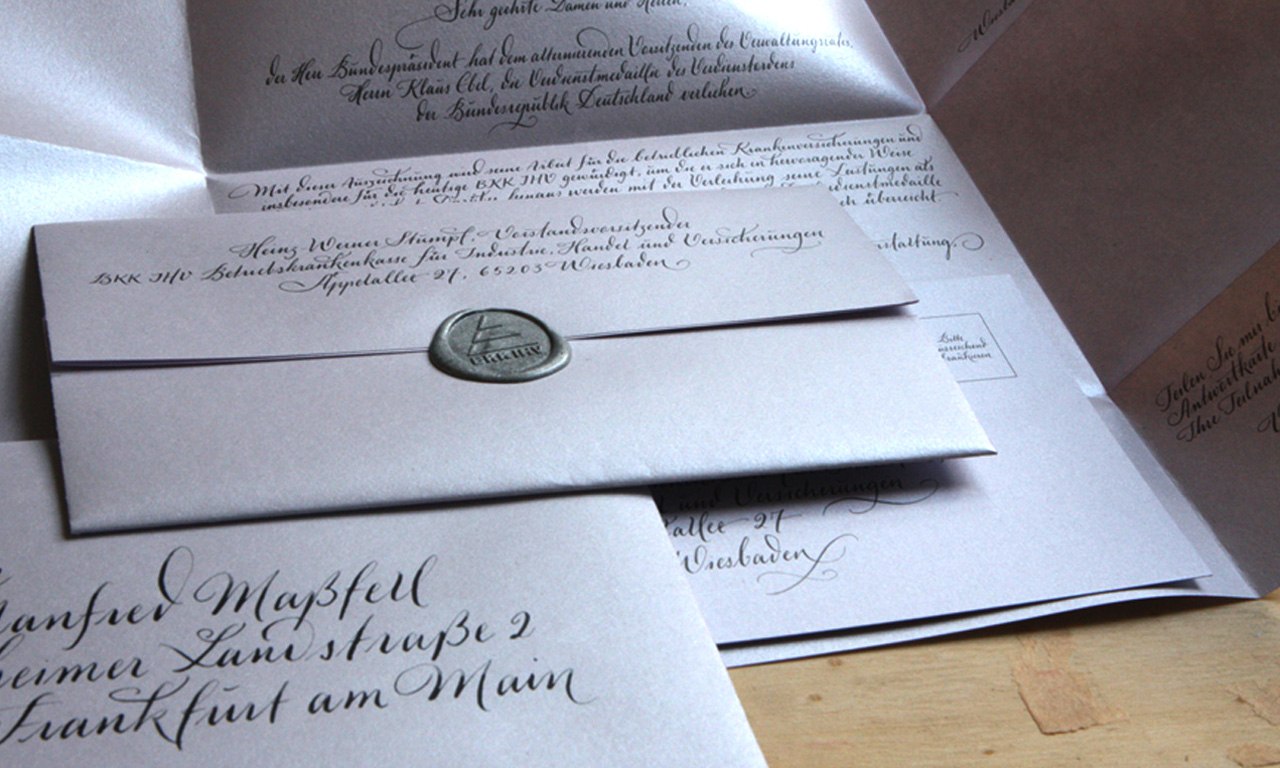
Exklusive Einladung
Designkonzeption, handschriftliche Umsetzung des gesamten Textes, Erstellung der Feindaten für Druck und Gravur, Produktionsabwicklung.
Handschriftliche Adressierung im Schriftduktus des Innenteils, Versiegelung der Auflage.